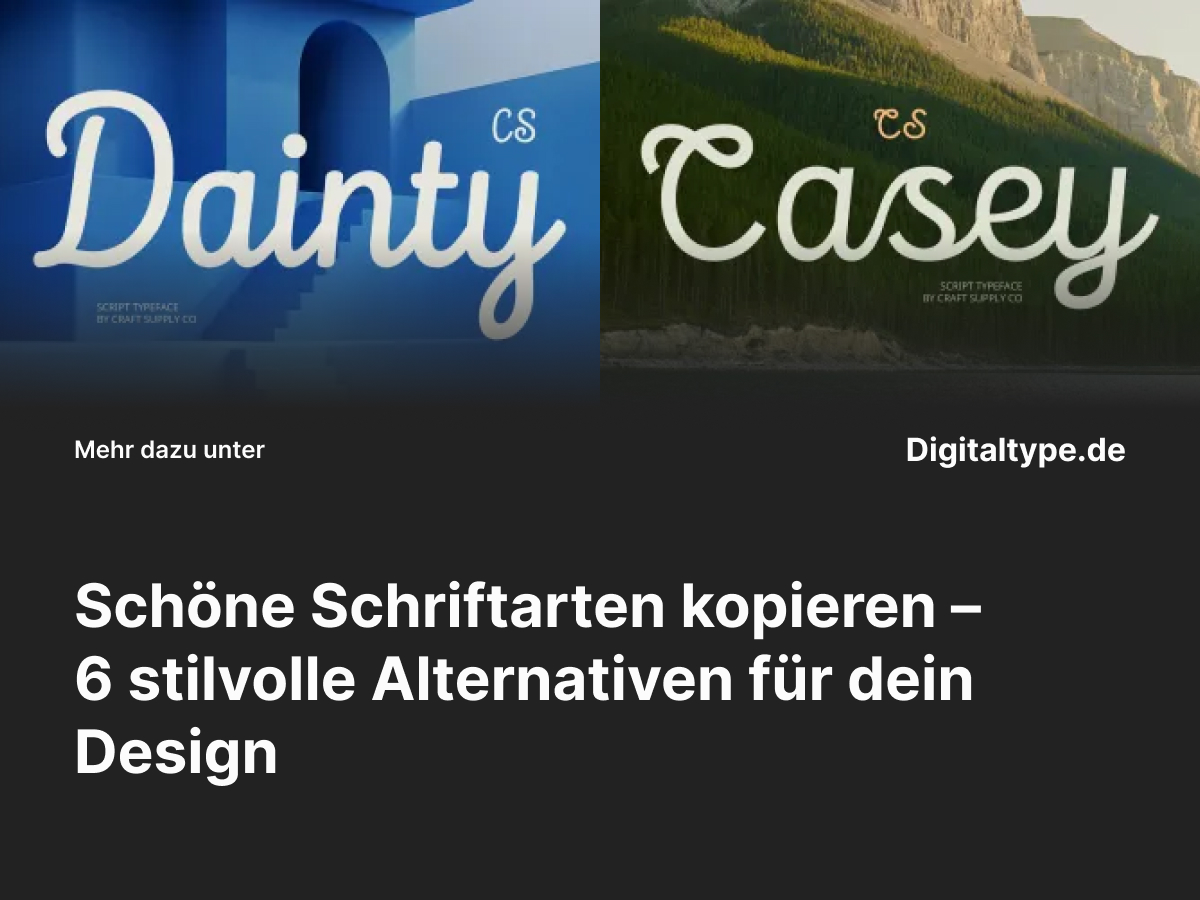
Wenn du nach schönen Schriftarten zum Kopieren suchst, möchtest du wahrscheinlich schnell und einfach an ästhetische Fonts kommen, die deine Designs aufwerten. Egal ob für Social Media, Logos, Einladungen oder kreative Projekte – die richtige Schrift verleiht deinem Werk Persönlichkeit und Wiedererkennungswert.
In diesem Artikel zeigen wir dir, was beim Kopieren und Verwenden schöner Schriftarten wichtig ist, welche rechtlichen Punkte du beachten musst und stellen dir sechs hochwertige Alternativen vor, die du sofort nutzen kannst.
Was bedeutet „schöne Schriftarten kopieren“ eigentlich?
Mit „Schriftarten kopieren“ ist oft gemeint, dass man Fonts aus dem Internet übernimmt, um sie in eigenen Projekten einzusetzen – sei es für private oder kommerzielle Zwecke. Dabei geht es nicht nur um das einfache Kopieren von Schriftstilen, sondern auch darum, sie richtig und legal zu verwenden.
Gestaltungstipps für schöne Schriftarten
- Kombiniere Kontraste: Eine verspielte Handschrift harmoniert wunderbar mit einer klaren Sans-Serif-Schrift.
- Beachte Lesbarkeit: Dekorative Fonts eignen sich eher für Überschriften oder kurze Texte.
- Weißraum nutzen: Mehr Abstand lässt handschriftliche Fonts eleganter wirken.
- Teste Größen: Prüfe, wie die Schrift auf unterschiedlichen Geräten aussieht – besonders auf mobilen Displays.
Die 6 schönsten Schriftarten zum Kopieren (Alternativen)
Hier findest du sechs sorgfältig ausgewählte Schriftarten zum Kopieren, die du für kreative, elegante oder handgemachte Designs nutzen kannst:
1. CS Dainty Script Font
CS Dainty ist eine elegante Script-Schrift mit sanften Linien und femininer Note. Ideal für Branding, Einladungen oder Social-Media-Posts, die einen hochwertigen Eindruck machen sollen. Die handschriftliche Struktur verleiht jedem Projekt eine persönliche Wärme.
2. CS Casey Script Font
CS Casey ist modern und fließend – perfekt für kreative Zitate, Lifestyle-Marken und Verpackungsdesigns. Die Balance aus Rundungen und Klarheit sorgt für ein stilvolles, professionelles Erscheinungsbild.
3. CS Alicent Script Font
CS Alicent kombiniert klassische Kalligrafie mit moderner Lesbarkeit. Sie eignet sich für elegante Logos, Hochzeitseinladungen oder edle Produktetiketten. Die schwungvollen Buchstaben wirken besonders charmant in großen Headlines.
4. Adevas Stamp Font
Adevas Stamp hat einen rauen, industriellen Charakter mit Vintage-Charme. Wenn du Retro- oder Grunge-Projekte umsetzt, ist diese Font die perfekte Wahl – authentisch, robust und individuell.
5. Quency Rough Font
Quency Rough bringt Handarbeit und Charakter zusammen. Die leicht unregelmäßige Textur macht sie besonders ausdrucksstark für Logos, Poster oder kreative Typo-Kompositionen mit Retro-Flair.
6. CS Bowie Script Font
CS Bowie ist eine dynamische, schwungvolle Schrift mit urbanem Stil. Sie vermittelt Energie und Kreativität – ideal für Musik- oder Lifestyle-Brandings, die auffallen wollen.
Wann du schöne Schriftarten einsetzen solltest
Schöne Schriftarten eignen sich besonders für:
- Social Media Grafiken (Instagram, Pinterest, YouTube Thumbnails)
- Einladungen und Hochzeitspapeterie
- Markenlogos und Produktverpackungen
- Zitate oder Moodboards mit persönlichem Stil
Nutze sie gezielt, um Emotionen zu transportieren und dein Design einzigartig zu machen.
Fazit
Eine schöne Schriftart zum Kopieren kann deinem Design sofort eine professionelle und emotionale Wirkung verleihen – aber nur, wenn du sie legal und bewusst einsetzt. Prüfe immer die Lizenz, kombiniere Schriften mit Bedacht und nutze hochwertige Fonts wie die oben genannten Alternativen, um deine Projekte auf das nächste Level zu heben.